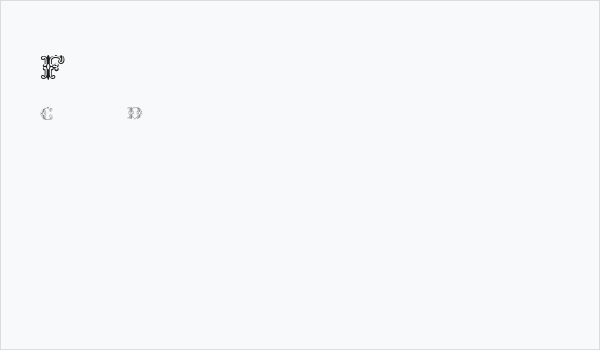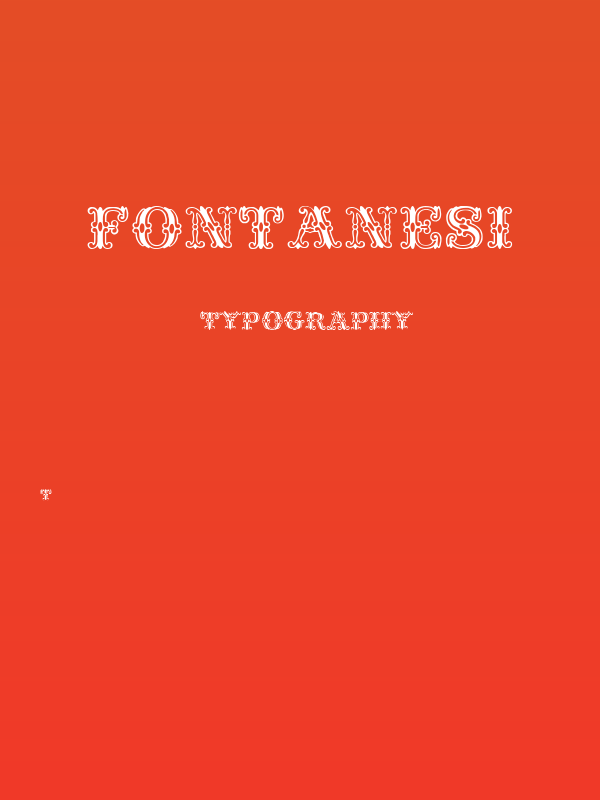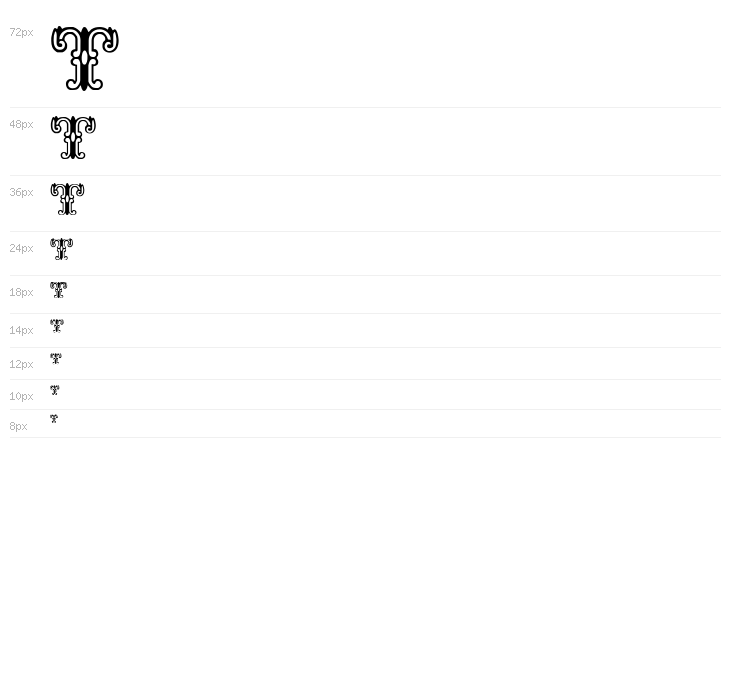
Fontanesi Font
| Progetti proposti | Ideal for wedding invitations, vintage-themed posters, branding for luxury products, or any project requiring a touch of elegance and sophistication. |